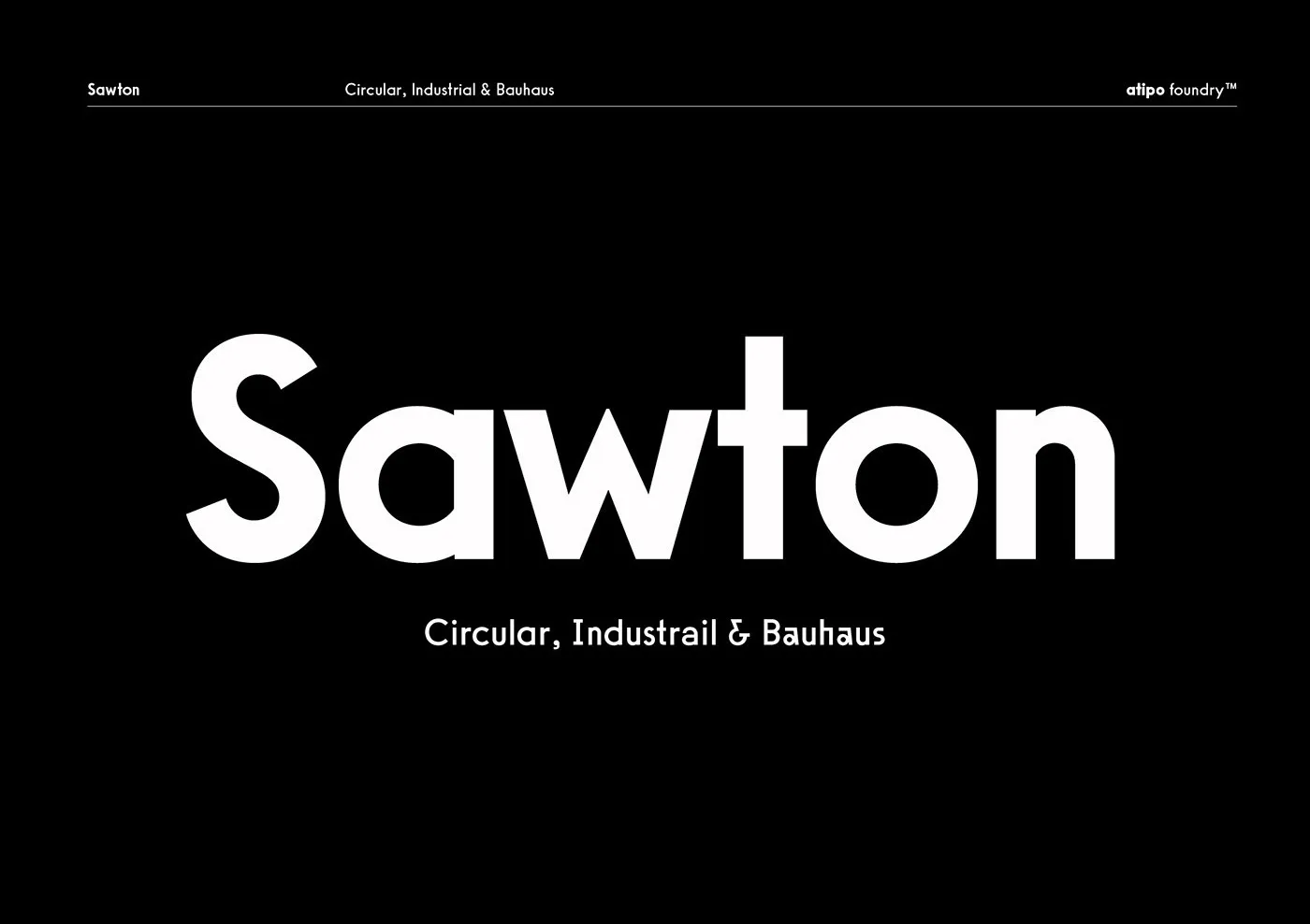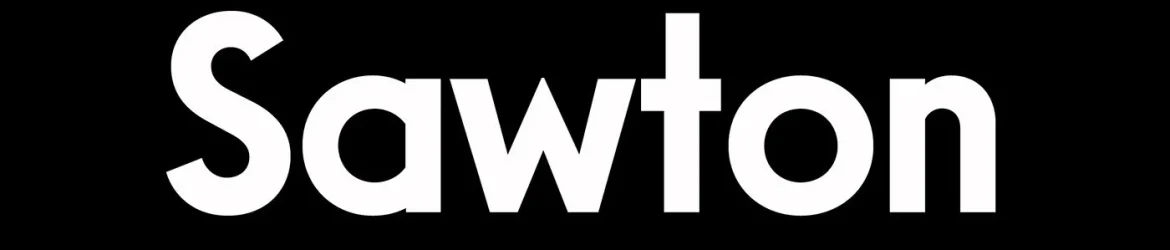
A fonte Sawton Font é uma escolha perfeita para qualquer designer que busca uma mistura única de simplicidade geométrica com um toque moderno e robusto. Desenvolvida pelo atipo, ela se destaca como um novo tipo de família geometricamente simétrico, totalmente sem serifas. Esta fonte é ideal para adicionar um ar fresco e moderno a qualquer projeto de design, combinando precisão geométrica com uma leveza e uma delicada imperfeição. Com três estilos distintos – Circular, Industrial e Bauhaus – Sawton oferece uma variedade única que pode ser usada isoladamente ou em composições conjuntas. Cada estilo tem sua própria personalidade, garantindo a funcionalidade tanto individual quanto coletiva. Ideal para uma ampla gama de aplicações, como marca identificação, criação de logotipos, sinalização, publicações editoriais, anúncios e embalagens, Sawton é um recurso versátil e poderoso em seu catálogo. Com 15 pesos diferentes – desde fino até grosso – a Sawton Font está pronta para transformar qualquer projeto, oferecendo uma variedade infinita de opções para se adequar às necessidades específicas de cada projeto.